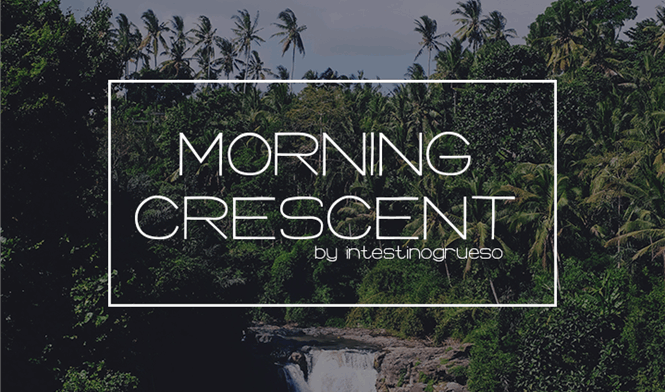
Morning Crescent font – Download Grátis
A Morning Crescent é uma fonte sans-serif criada por Hamilton em 2015. Esta fonte é gratuita para uso pessoal, mas os donativos são muito apreciados pela comunidade de designers que a contribuiu ao longo do tempo. Intendido principalmente para designers gráficos e desenvolvedores de sites, essa família de letras oferece um estilo limpo e moderno que se destaca por sua simplicidade. É perfeitamente adequada para criar designs que requerem uma aparência clean e minimalista, seja em sites profissionais ou no design editorial. Companheira ideal do Proxima, outra fonte sans-serif, a Morning Crescent é uma escolha confiável para quem busca um estilo moderno sem perder a presença visível da sua mensagem.